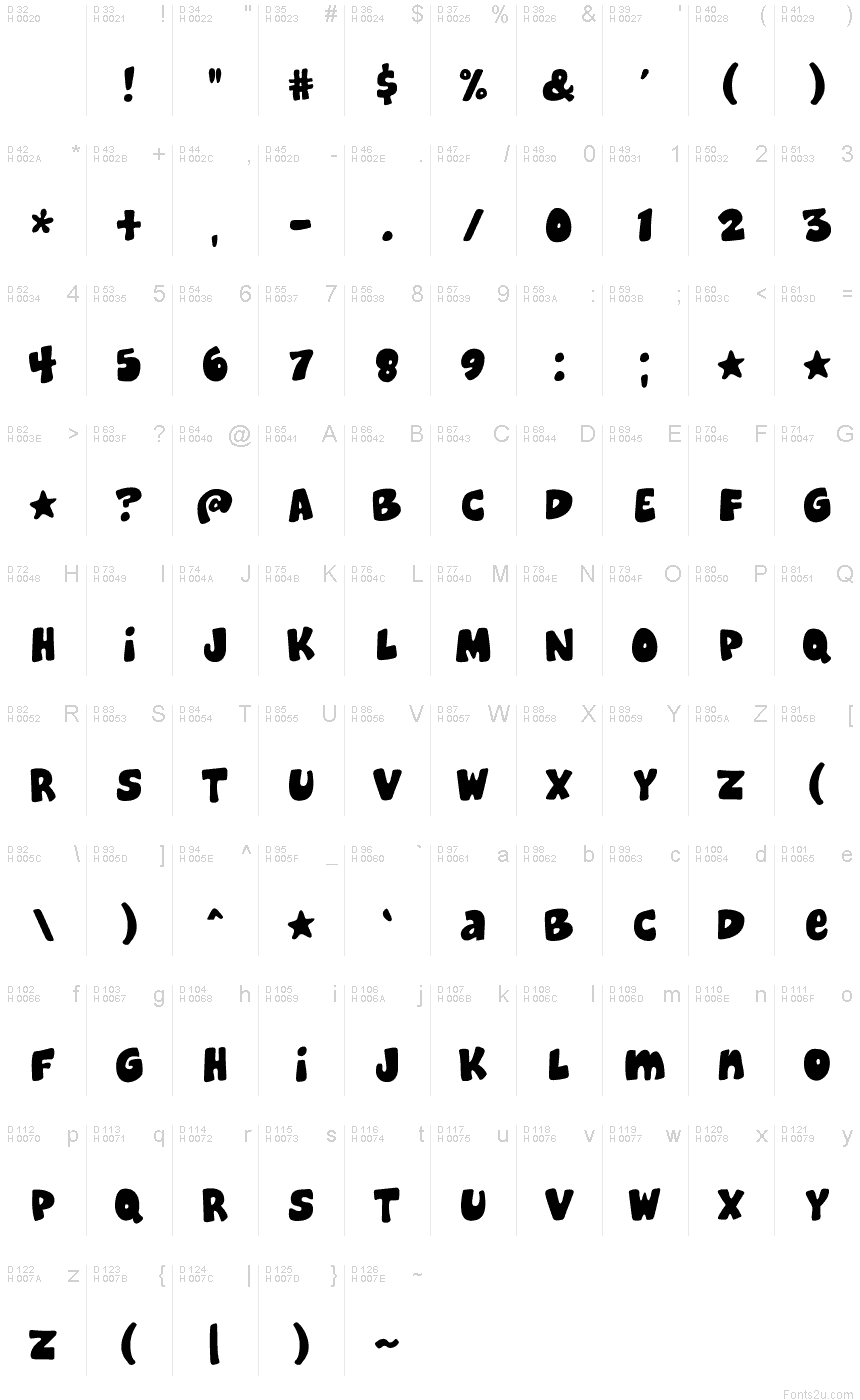
Cheeseburger di Fontalicious Fonts è un font display gratuito in stile fumetto che sembra tracciato con un sac-à-poche. Le sue lettere corpose e arrotondate hanno quel leggero tremolio che le rende naturali, come le scritte giocose su un food truck o uno striscione per feste. Le forme inchiostrate e quasi sciolte creano blocchi di testo d'impatto, che risultano divertenti e amichevoli senza essere troppo invadenti.
Con Cheeseburger, i titoli diventano subito gommosi, giocosi e un po' birichini: l'ideale per menu per bambini, packaging di snack, inviti, titoli di fumetti, copertine di video YouTube e branding di giocattoli. Questo font gratuito dà il meglio di sé nei grandi formati, dove le sue curve morbide risaltano al massimo, e si abbina perfettamente a un carattere sans serif geometrico per il testo di accompagnamento.